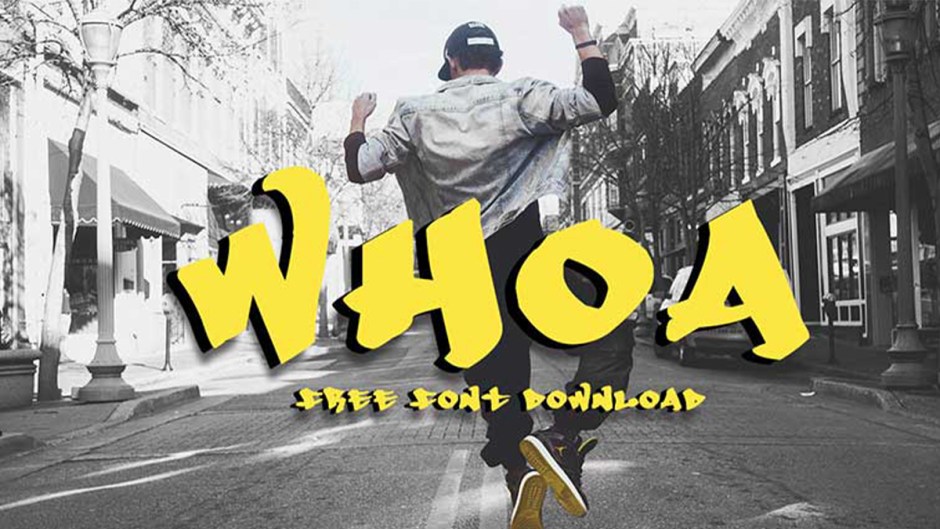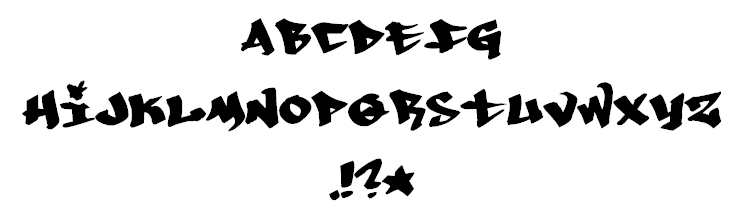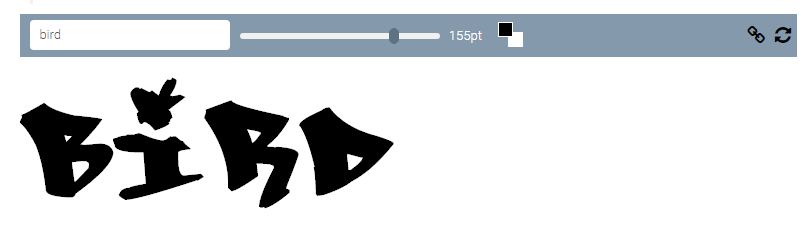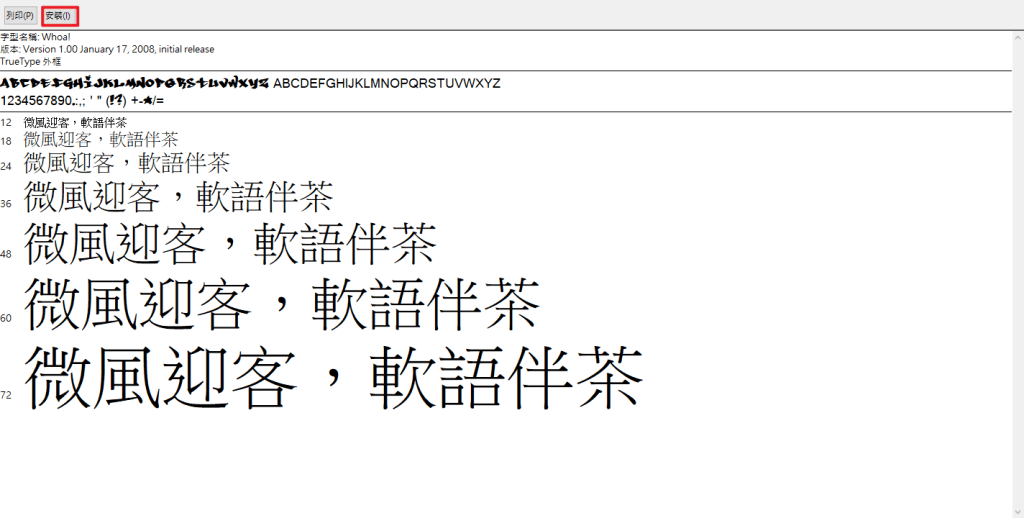
菜鳥救星分享:免費字體下載-Whoa 發佈日期: 2021-01-142022-11-25 作者: Natty 文、菜鳥編 今天要介紹一款很有嘻哈風的字體,名稱也相當好記,就是「哇」!字體粗體的表現相當吸睛,在強調的效果上相當好用,一款值得收藏的字體。 字體名稱:Whoa下載位置:http://bit.ly/2URW70W 進到網頁可以看到字體的表現,其中字母「I」的表現還使用了手指頭,相當俏皮。 大家關心的是否可商業使用,在網站上也有聲明。 在授權聲明的上方 就可以看到下載點,下載量也是相當驚人。 網站提供測試功能,可先將你要使用的內容輸入查看效果,滿意在下載。 下載下來的為壓縮檔,壓解縮後可以看到3個檔案。 在文字檔中的連結可開啟至開發者網站,本身除了字體外,對於音樂、平面設計的創作都有不錯的表現,不妨去支持一下。 字體的安裝也很簡單,只要開啟後安裝即可。 免費字體為網路搜尋而來,使用權限請以官方文件與說明為主 加入菜鳥救星官方Line並回覆「我想看文章」,不定期獲得更多知識吧! 不同頻道,不同知識! Facebook Instagram Youtube 分享此文: 分享到 X(在新視窗中開啟) X 分享到 Facebook(在新視窗中開啟) Facebook 分享到 Telegram(在新視窗中開啟) Telegram 以電子郵件將連結傳送給朋友(在新視窗中開啟) 電子郵件 請按讚:喜歡 正在載入... 相關